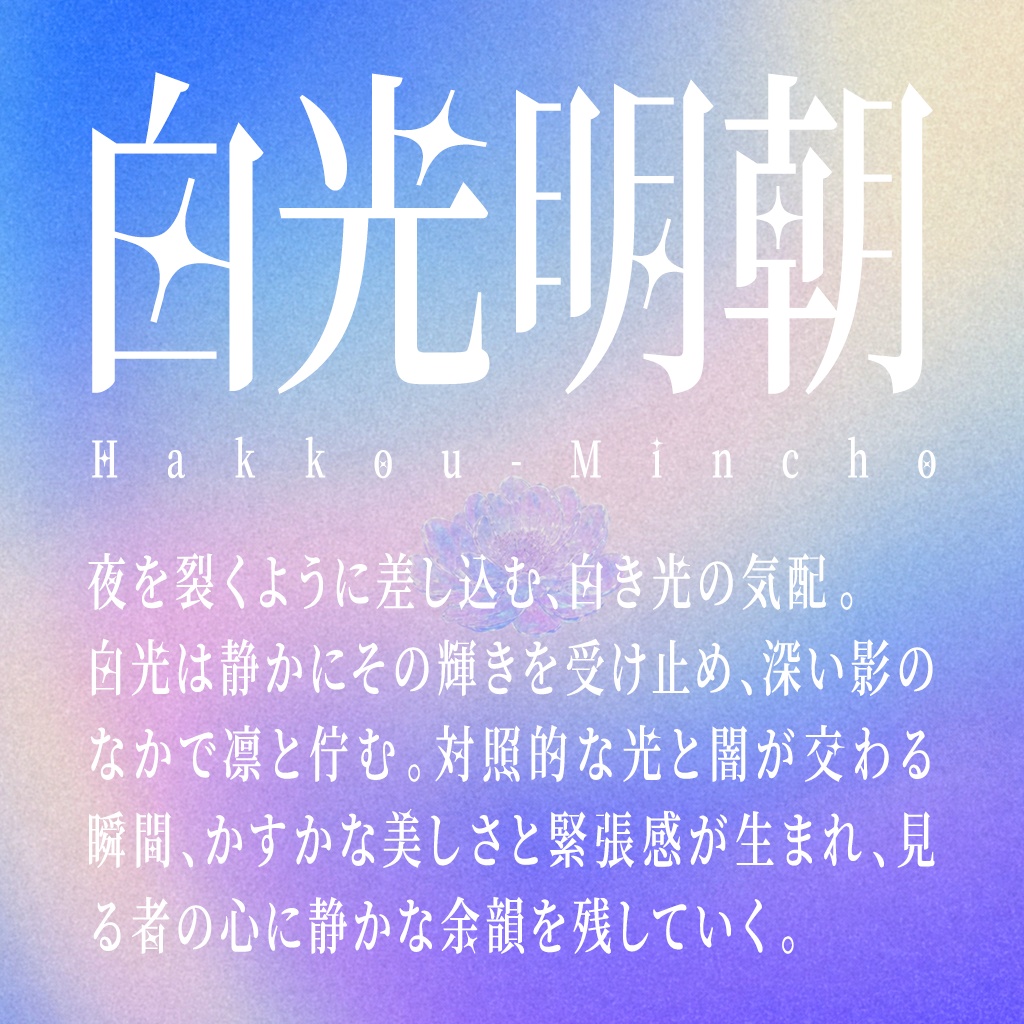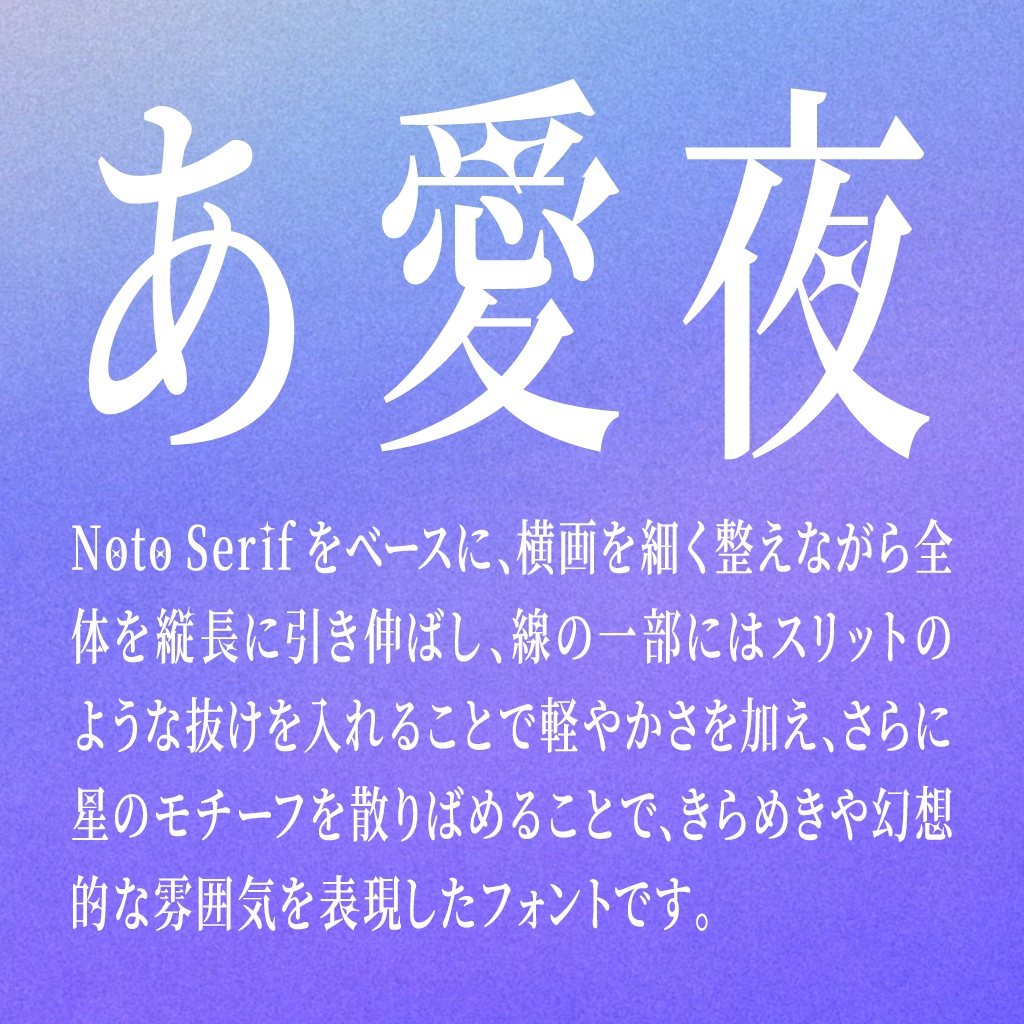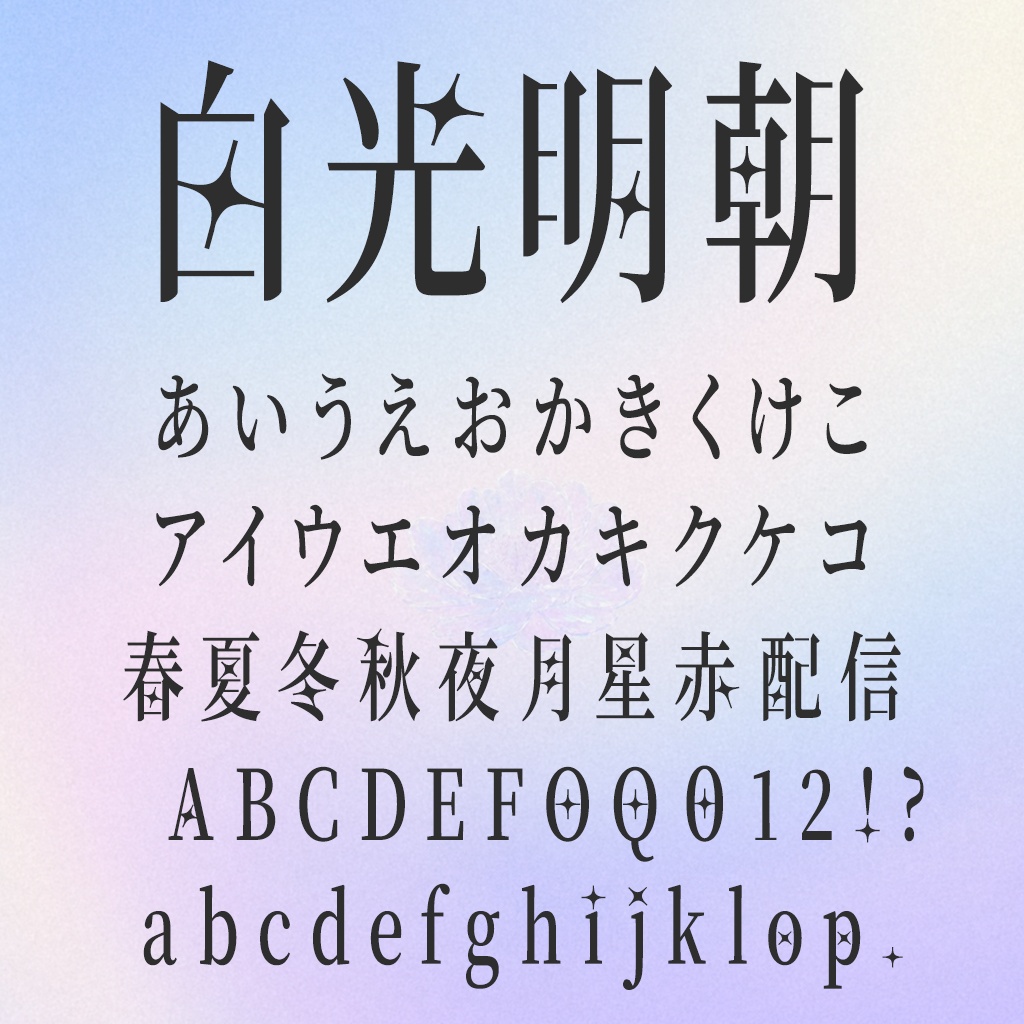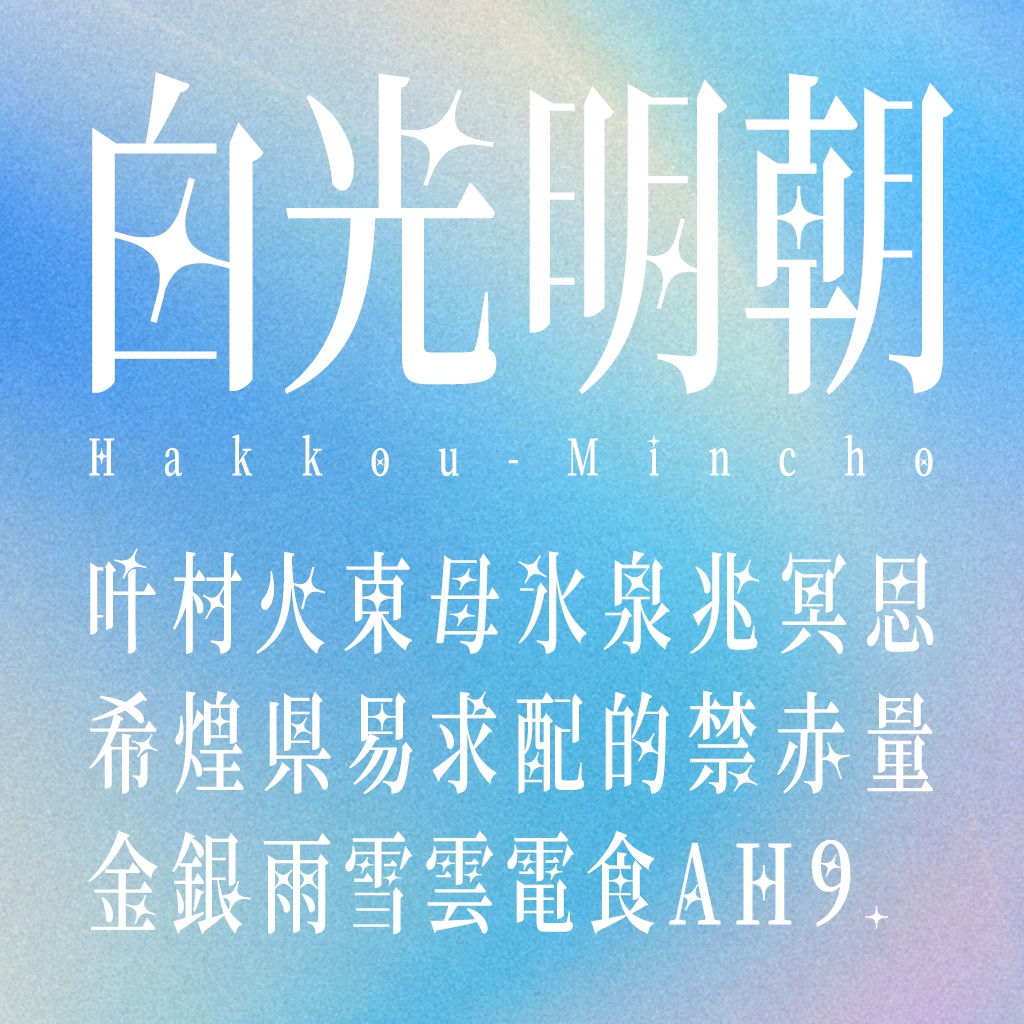
白光明朝
白光明朝(Hakkou Mincho)是一款以日版思源宋体Noto Serif 为基础进行改造的日系风格明朝体字体。字体没有延续传统明朝体端庄厚重的视觉印象,而是通过细化横画、拉伸字形比例以及调整笔画细节,让整体文字呈现出更加纤细、修长且轻盈的视觉效果。
在字形设计上,白光明朝将文字整体向纵向延展,使汉字拥有更加明显的高挑比例,同时弱化部分横向笔画的厚重感,让字体在大字号使用时呈现出清秀而富有张力的效果。部分笔画内部还加入了类似裂隙与切口的镂空处理,在保证基本字形结构的同时,为文字增加了一种通透、轻盈的感觉,也让整套字体形成了鲜明的视觉辨识度。
白光明朝最特别的地方,还在于它将星星元素融入了部分文字之中。设计者在字符内部随机加入星形装饰,让星光仿佛隐藏在笔画之间,在普通的文字排列中产生若隐若现的闪耀效果。星形细节并不会出现在每一个字符中,而是以随机的方式散布于部分文字,因此实际排版时也会带来一些意外的趣味性。
这种设计让白光明朝拥有非常鲜明的幻想气质。纤细修长的字形搭配星星般的装饰细节,既有明朝体本身所带来的古典感,又加入了更加轻盈、浪漫和神秘的视觉语言。尤其是在深色背景、渐变色彩或带有夜空、星辰元素的设计中,能够很好地表现出一种安静而梦幻的氛围。
从字符表现来看,白光明朝支持日文平假名、片假名,同时收录中文汉字、英文字母、数字以及常用标点等字符,可以满足日常设计中的中日文混排需求。中文字符共收录4547个,能够覆盖较为常见的中文文字使用场景。英文字母同样采用纤细、修长的衬线结构,与中文及日文字符保持统一的视觉气质,在标题、短句以及海报等大字号排版中具有较强的装饰表现力。
白光明朝更适合用于海报标题、书籍封面、音乐视觉、游戏设计、视频字幕、品牌视觉以及日系幻想风格的平面设计。它并不是一款追求传统正文阅读体验的常规明朝体,而是一款更强调字体本身视觉表现力的展示字体。当文字被放大之后,纤细的笔画、特殊的镂空结构以及隐藏其中的星形元素都能够更加清晰地展现出来,让字体成为画面氛围的一部分。
白光明朝并没有刻意追求传统明朝体的规整与厚重,而是将纤细的笔画、修长的字形、独特的镂空以及星光般的装饰融合在一起,让熟悉的明朝体呈现出更加轻盈、梦幻的一面。如果你正在寻找一款能够表现星辰、幻想、浪漫与神秘感的日系展示字体,白光明朝会是一款很有特色的选择。